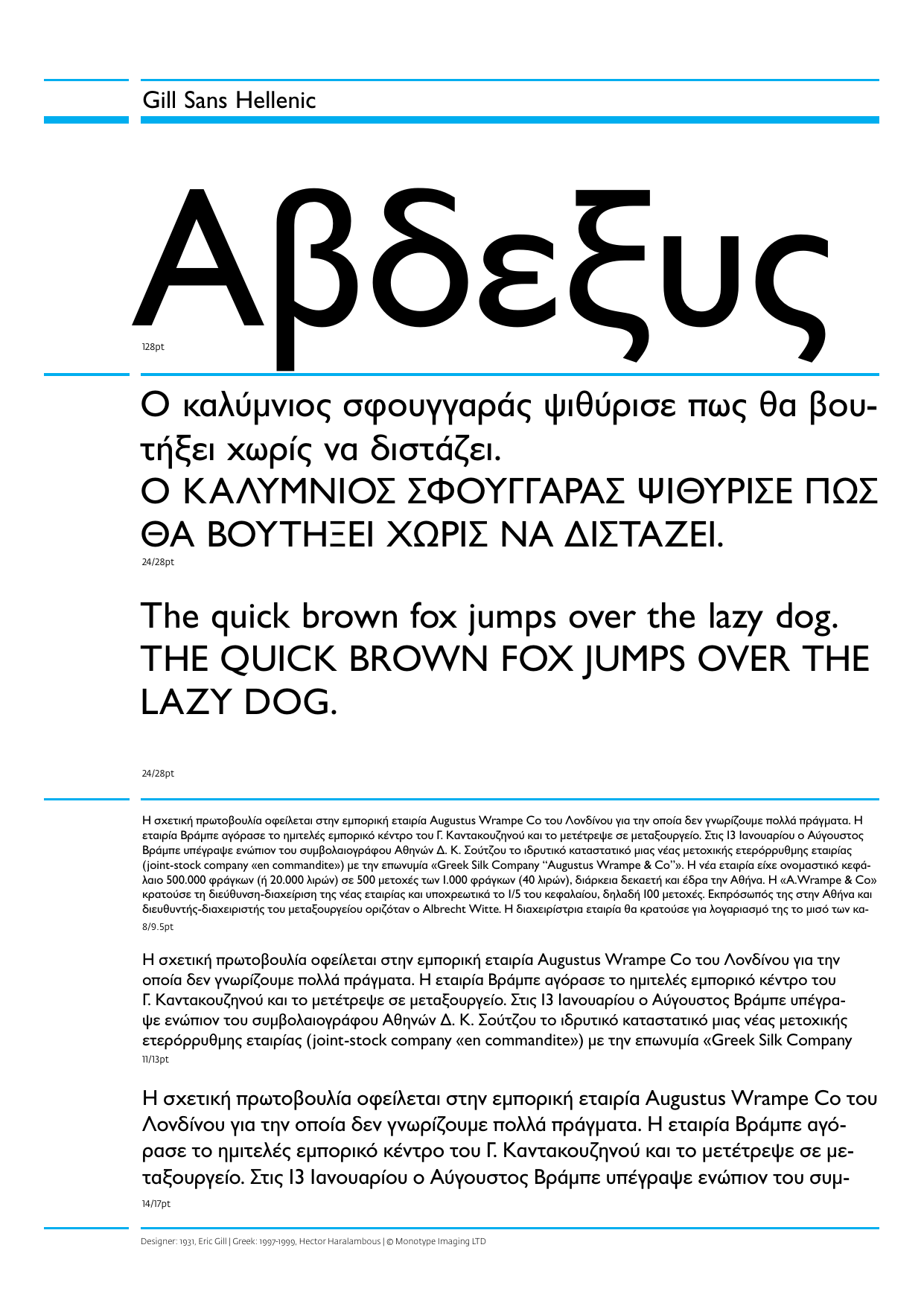
Gill Sans Ελληνικά Collection
Οι ρίζες της Gill μπορούν να αναζητηθούν σε Old Face γραμματοσειρές και πιο συγκεκριμένα σε αυτές που σχεδίασε ο δάσκαλός του Gill, Edward Johnston για λογαριασμό του London Underground. Αποπνέει μία μοντέρνα αίσθηση και μία καθαρότητα και διαθέτει πλήθος βαρών και παραλλαγών. Στην Ελλάδα είναι εξίσου δημοφιλής καθώς υπήρξε η επίσημη γραμματοσειρά για τους Ολυμπιακούς Αγώνες της Αθήνας το 2004.